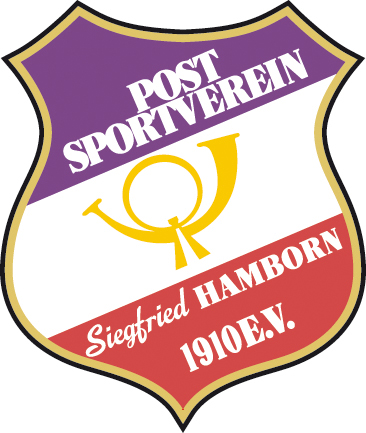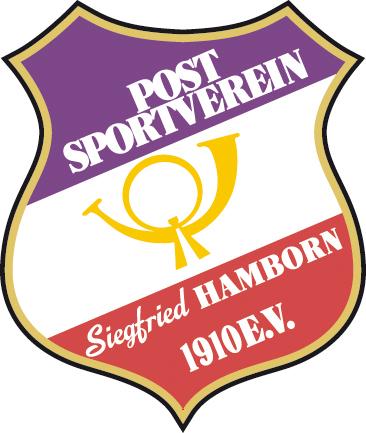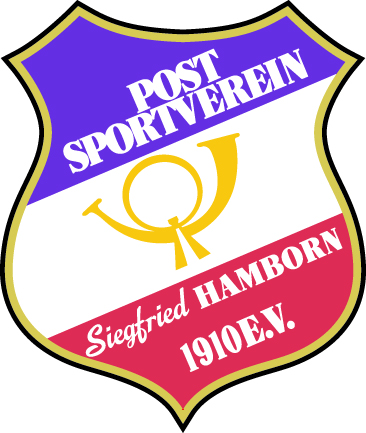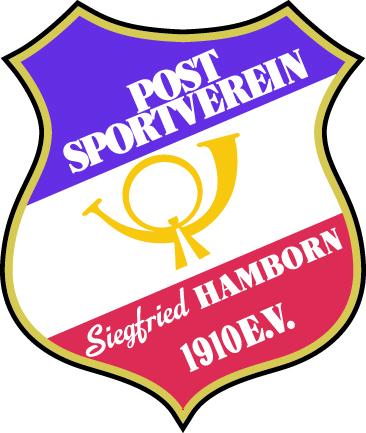
Wappen von Post Siegfried Hamborn
Ich weiß die Schriftnamen leider nicht ad hoc, aber ich würde Euch empfehlen, beim Nachbau des Zeichens dann auch gleich die typografischen Fehler – beziehungsweise Unstimmigkeiten – zu korrigieren.
Für den Fall, dass Euch das Thema interessiert und Ihr das Zeichen optimieren wollt, hier ein paar Tipps: Zwischen 1910 und das E gehört ein ganzes Leerzeichen und zwischen den Punkt und das V gehört ein kleiner Abstand (normalerweise wird das e außerdem kleingeschrieben). Außerdem würde ich Euch empfehlen, die Texte alle in einer einheitlichen Größe zu setzen und die Versalien (Großbuchstaben) leicht zu sperren, was bedeutet, die Buchstaben mit etwas mehr Zwischenraum zueinander zu setzen. Als nächstes müssten die Zeilenabstände dringend ausgeglichen werden – im violetten Bereich sitzen die Worte zu dicht aufeinander, im roten Bereich ist viel zu viel Luft zwischen den Zeilen. Im weißen Bereich müsste das Posthorn mit Augenmaß korrekt ausgemittelt werden – jetzt wirkt es wie versehentlich hochgerutscht. Der »Siegfried« sitzt zu dicht am linken Rand, mal ganz davon abgesehen, dass er durch die andersartige Schriftart im Gesamtzusammenhang wie ein Fremdkörper wirkt.
Habt Ihr eine grafisch versierte Person an Eurer Seite, die das Zeichen für Euch in Vektoren umsetzt? Dann könntet Ihr diese auch gleich um die Korrekturen bitten.  :-D
… bei der Gelegenheit könnte man auch gleich noch das fehlende Divis zwischen POST und SPORTVEREIN ergänzen und den Mißstand beheben, daß 1910 aus einer anderen Schrift gesetzt wurde als HAMBORN E.V.. Will man es nicht nur richtig haben, sondern auch noch hübsch, müßte man freilich auch noch über die Farben nachdenken. ;-)
Und einem Experten in Wappenkunde würde sicherlich auch noch die ein oder andere Anmerkung einfallen. Aber da ist ja auch die Frage, wie sehr das Ganze in die Tiefe gehen soll oder ob es nicht einfach nur um ein ansprechendes Zeichen geht, das einprägsam ist und Tradition vermittelt. Nur mal eine Frage aus reiner Neugier an den Threadersteller: Was hat es denn mit den Farben auf sich? Stehen sie in diesem Vereinszeichen für etwas Bestimmtes?  :-)
POST SPORTVEREIN HAMBORN E.V. ist aus der Caslon Black.
Das ist ein cmyk-jpg (warum auch immer?), die rgb-Entsprechung sähe so aus:
Falls Du damit auf meine Frage eingehst – ich meinte eher die inhaltliche Bedeutung der Farben. Also warum ausgerechnet Rot und Violett für diesen Sportverein?
Ah, nein, das war eine Antwort auf Pachulkes "… müßte man freilich auch noch über die Farben nachdenken.:gimmifive:
Die ursprünglich dargestellt sind schon etwas laut, aber das fußt auf dem falschen Farbraum. Wobei ich mir sogar vorstellen kann, dass das Lila ganz früher mal ein Blau war …
Wenn man auf die Website des Sportvereins schaut, dann ist das Violett die alles bestimmende Farbe des Vereins. Und außerdem scheint mir das ein sehr netter Sportverein zu sein – der auch gleich ein Freundschaftsspiel mit Flüchtlingskindern organisiert hat. Finde ich gut!  :nicken:
Wo ich mir das »Siegfried« des gezeigten Zeichens gerade genauer anschaue, habe ich irgendwie das Gefühl, dass das »S« gar nicht zum »iegfried« gehört, kann das sein? Und die Unterlängen von g und f passen nicht wirklich gut zusammen und das r sieht auch merkwürdig aus. Wäre es möglich, dass das Wort aus verschiedenen Schriften zusammengesammelt wurde? Auf alle Fälle erhält man bei MyFonts jede Menge ähnliche Schriften, wenn man »Sign Painting« als Suchbegriff eingibt.
Bis auf S und f sieht das nach Script MT aus. Vielleicht gefielen die beiden Zeichen nicht und es wurden passende™ gebastelt ..?
Edit: und das r natürlich auch …
Und einem Experten in Wappenkunde würde sicherlich auch noch die ein oder andere Anmerkung einfallen.
Ich ernenne mich hiermit selbst zu einem.  :huhu:
Ganz unbeschadet der Frage, ob das jetzt ein Wappen im klassischen Sinn ist:
Ihr würdet ein Wappen nicht wirklich verändern, wenn es neu gezeichnet wird und es dadurch zu einer abweichenden Linienführung bei ansonsten gleichem Inhalt kommt, das ist dann immer noch dasselbe Wappen, nur in modifizierter grafischer Ausführung.
Das bedeutet für den vorliegenden Fall: Seid doch mutig und setzt die Schriften unter Berücksichtigung der vielen hier gemachten Vorschläge neu, oder besser noch, lasst es von jemandem, der’s gut kann, für einen kleinen Taler machen.
Das ist übrigens etwas sehr traditionelles, was die Väter und Mütter des Vereins ganz sicher auch gemacht haben, denn das Zeichen ist in der vorliegenden Form bestimmt nicht von 1910, sondern seitdem auch schon (vielleicht sogar mehrmals?) neu gezeichnet.
Und außerdem scheint mir das ein sehr netter Sportverein zu sein –
der auch gleich ein Freundschaftsspiel
mit Flüchtlingskindern organisiert hat.
Da tut sich gottlob zur Zeit sehr viel in den Sportvereinen.
Zum Beispiel hier:
Ich bin erschlagen worden mit Ratschlägen....
damit habe ich ehrlich gesagt nicht gerechnet.
Nun denn, das Wappen ist vor über 100 Jahren tatsächlich so in den Farben erstellt worden.
Dies beruht sich auf die Fusionen mehrer Vereine von damals.
Die Schrift ist sicherlich x-mal überarbeitet worden davon gehe ich einfach mal aus.
Ich bin eigentlicxh sogar der Meinung, dass weder auf Wappen, Verkehrszeichen, Markenlogos und Vereinslogos Text drau sein sollte, wenn irgend möglich. Es immer ziemlich deutlich, das die führenden Marken textlos sind, während, je kreisklassiger das wird, immer reichlicher Text in den Logos zu finden ist.
Ich könnte mir sehr gut vorstellen, dass dies für die Wiedererkennung des Vereins völlig ausreichen würde: